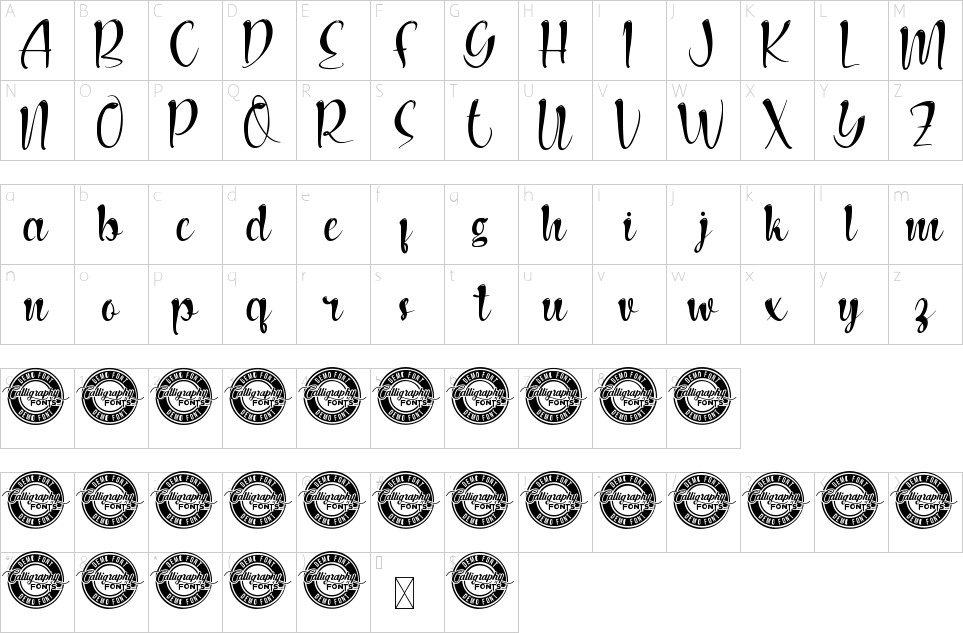
Descubra Glowing Skin Font, uma fonte única e vibrante para seus projetos digitais. Especialmente adaptada aos designers que buscam criar ambientes agradáveis e vivos, essa fonte traz uma textura luminosa e quente que pode enriquecer o visual de qualquer layout ou design. Desenvolvida pela equipe da CalligraphyFonts, Glowing Skin tem sido amada por usuários de todos os níveis de expertise. Com seu estilo chamativo e sua capacidade de criar um impacto imediato em seu design gráfico, essa fonte é certamente uma excelente escolha para adicionar um toque especial aos seus projetos. Compre Glowing Skin Font hoje e transforme o modo como você visualiza texto com sua textura luminosa e quente que brilha nos seus designs digitais.